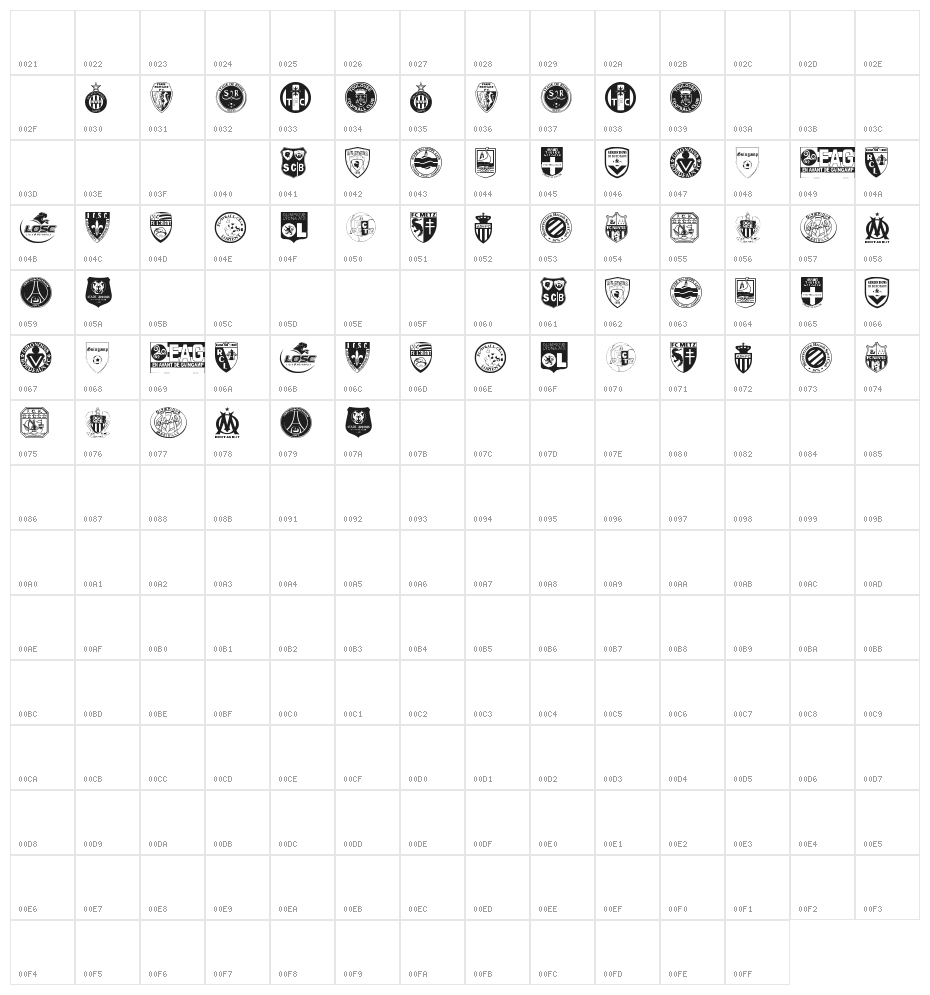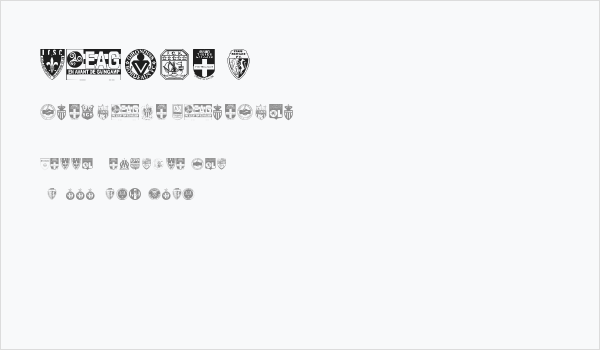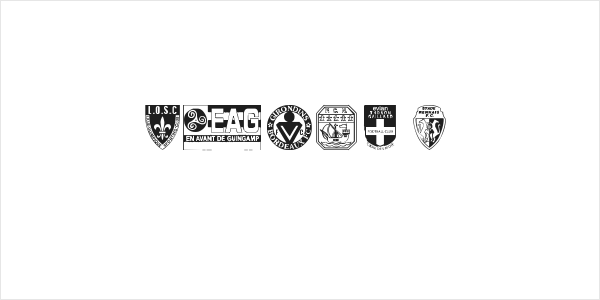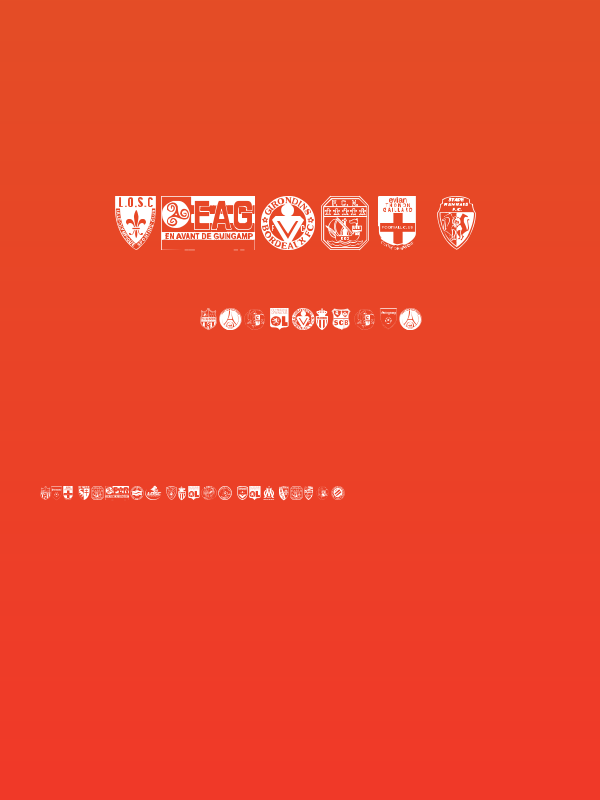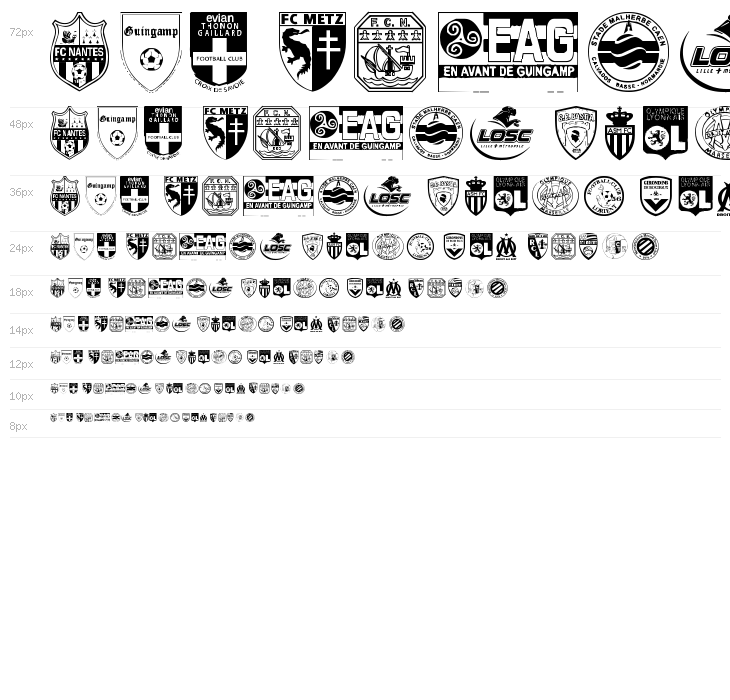
Ligue 1 Font
| Общий стиль | Sporty, Emblematic, Traditional |
| Область применения | Team logos, Sports branding, Merchandise |
| Рекомендуемые проекты | Sports branding, team merchandise, sports websites, fan art, and promotional materials. |